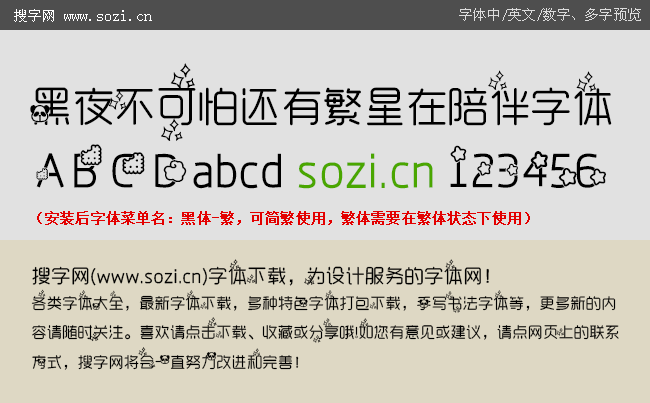
黑夜不可怕還有繁星在陪伴字體
搜字網(wǎng)給大家提供一款充滿童趣的手機(jī)中文字體下載。這款手機(jī)字體是在造字工房悅黑體字體筆畫間插入了可愛星星圖案。趣味性實足,名字叫黑夜不可怕還有繁星在陪伴字體,這款字體即帶有悅黑的簡約風(fēng)格,又有星星點綴的童趣,喜歡的朋友就裝上用用吧。